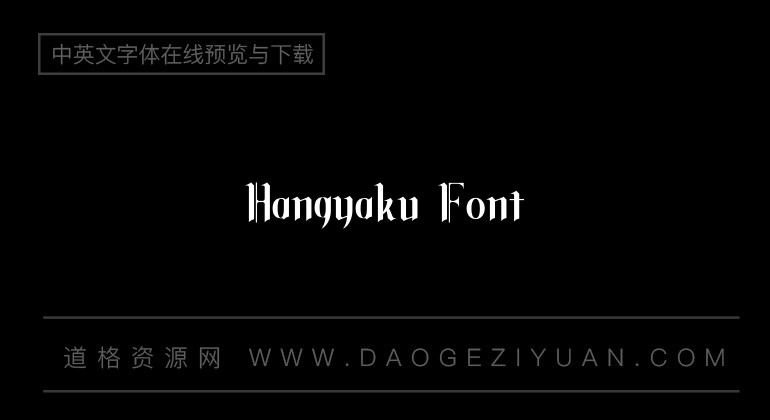
Hangyaku Font(叛逆字体)是一种由日本设计师Tomoyuki Watanabe创建的免费字体。这个字体的特点是每个字形都带有一些刻意的不规则线条和不对称元素,使它看起来有点叛逆和独特。 这个字体的设计灵感来自于日本的涂鸦文化和街头艺术,它的字形大多数都是手写的,给人一种随意和自由的感觉。Hangyaku Font的设计风格非常适合用于印刷海报、插画、设计包装等艺术创作中。 Hangyaku Font支持英文字母、数字以及一些标点符号,但不支持汉字和其他语言文字。这个字体非常适合那些喜欢叛逆和独立精神的艺术家和设计师使用。内容介绍
Hangyaku Font是一款非常不错的手写艺术字体,具有很好的视觉感,适合于文化类的宣传设计、商业类品牌的广告和产品包装设计以及个性化文字排版等较多场景。